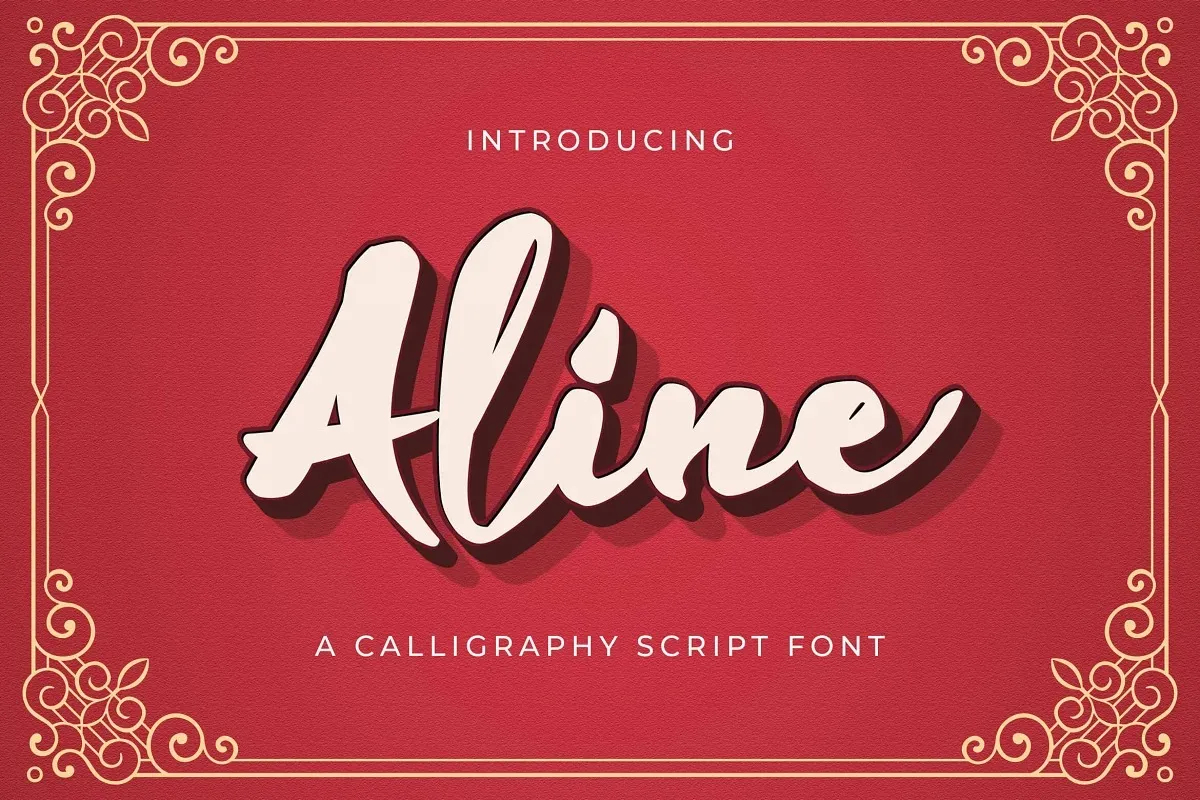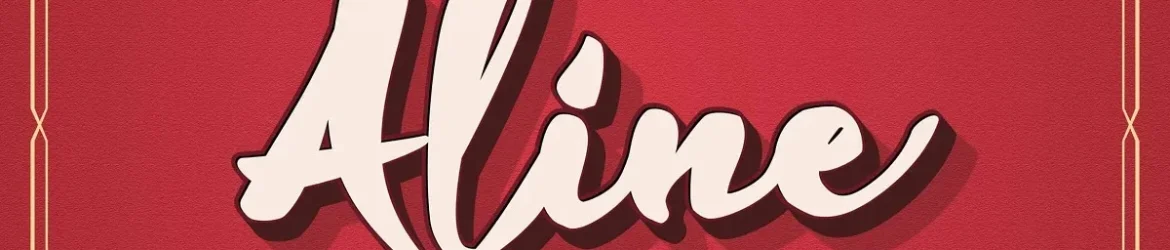
A fonte ‘Aline Font’ criada pela StringLabs é uma elegante e romântica tipografia de display, perfeitamente adaptada para trabalhos criativos. Com um equilíbrio perfeito entre cada caractere, esta font se destaca como ideal para design gráfico de alta qualidade. Seu uso em projetos modernos e arrojados promove uma conexão harmônica que transforma ideias inovadoras em realidade visualmente atraentes. Perfectamente adaptada para criações artísticas e criativas, Aline Font está pronta para revolucionar o seu trabalho de design.